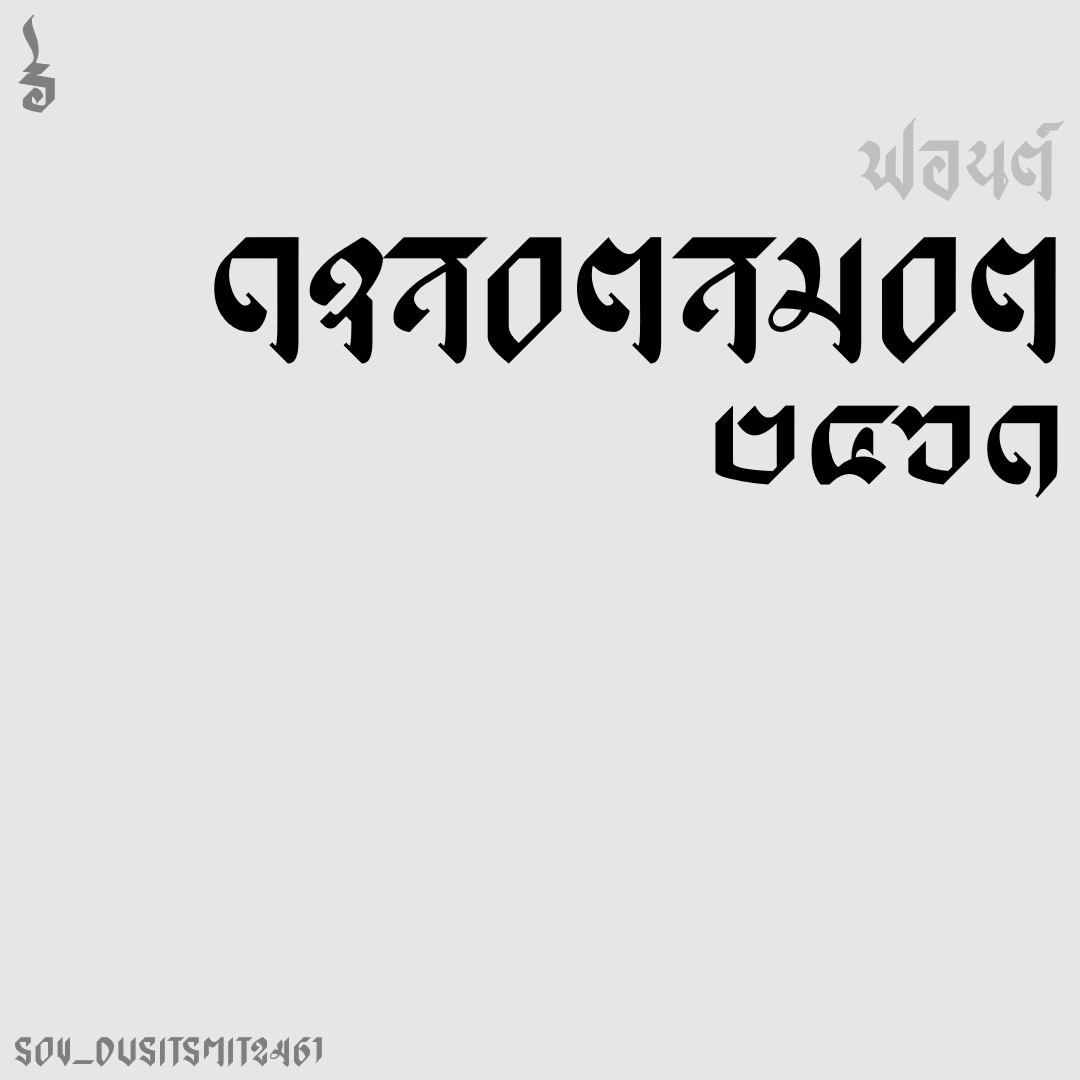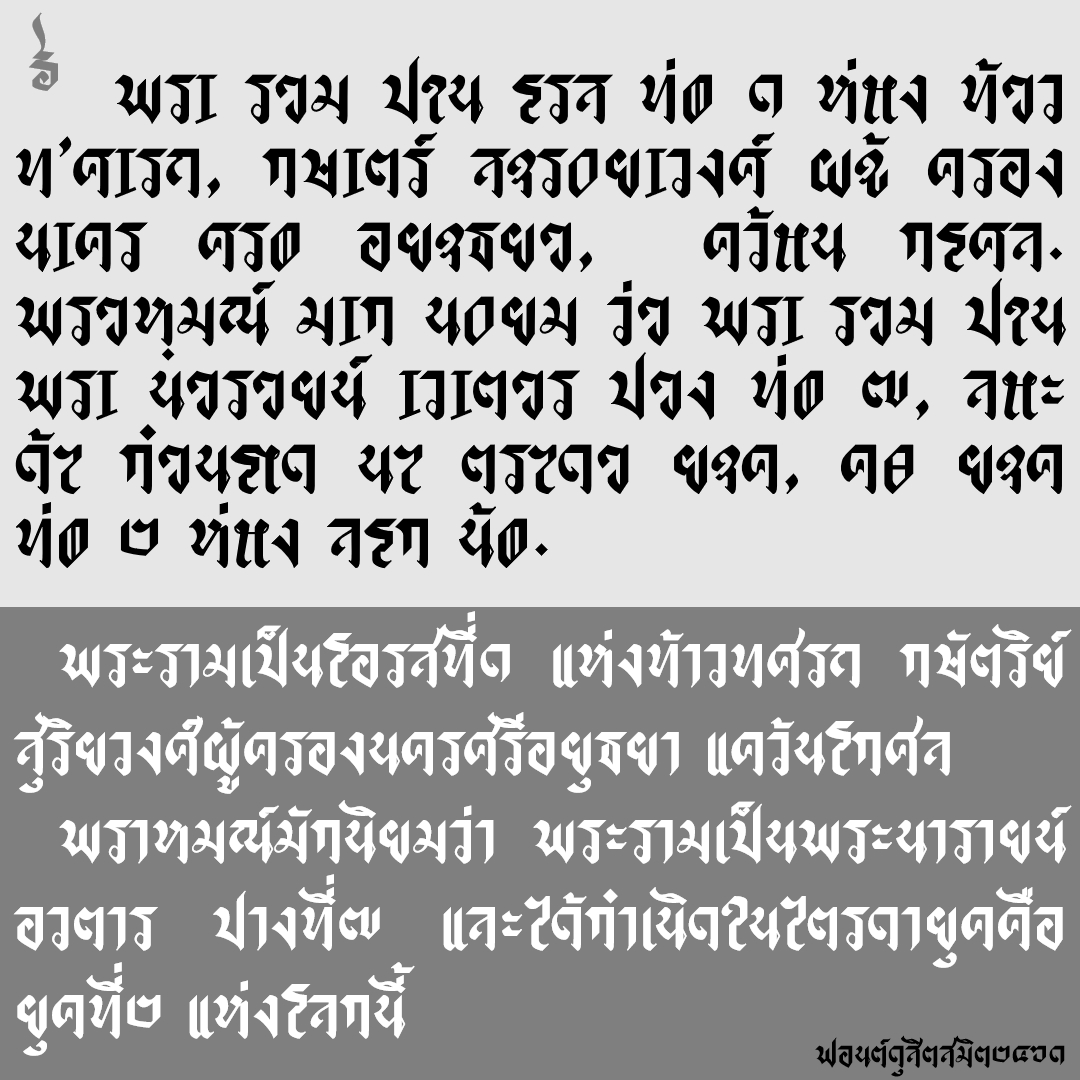
ฟอนต์ ดุสิตสมิต๒๔๖๑
ต้นแบบจากหัวหนังสือพิมพ์ "ดุสิต สมิต" เมื่อปีพ.ศ. ๒๔๖๑ เขียนด้วยอักขรวิธีใหม่สมัย ร.6
เอกสารอ้างอิง ดุสิตสมิต เล่มที่ ๑
ชื่อฟอนต์ : ดุสิตสมิต๒๔๖๑
ต้นแบบจากหัวหนังสือพิมพ์ "ดุสิต สมิต" เมื่อปีพ.ศ. ๒๔๖๑ เขียนด้วยอักขรวิธีใหม่สมัย ร.6